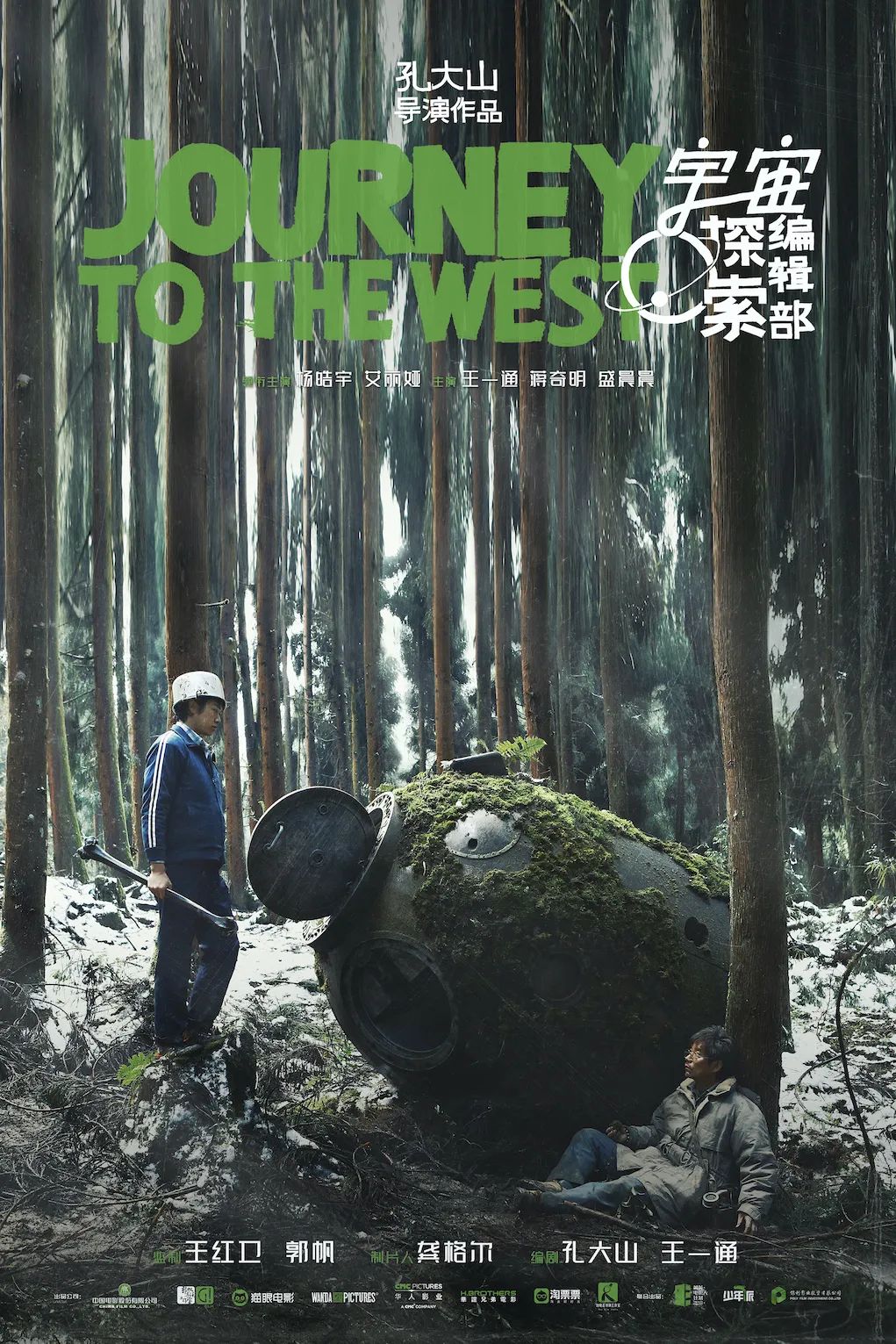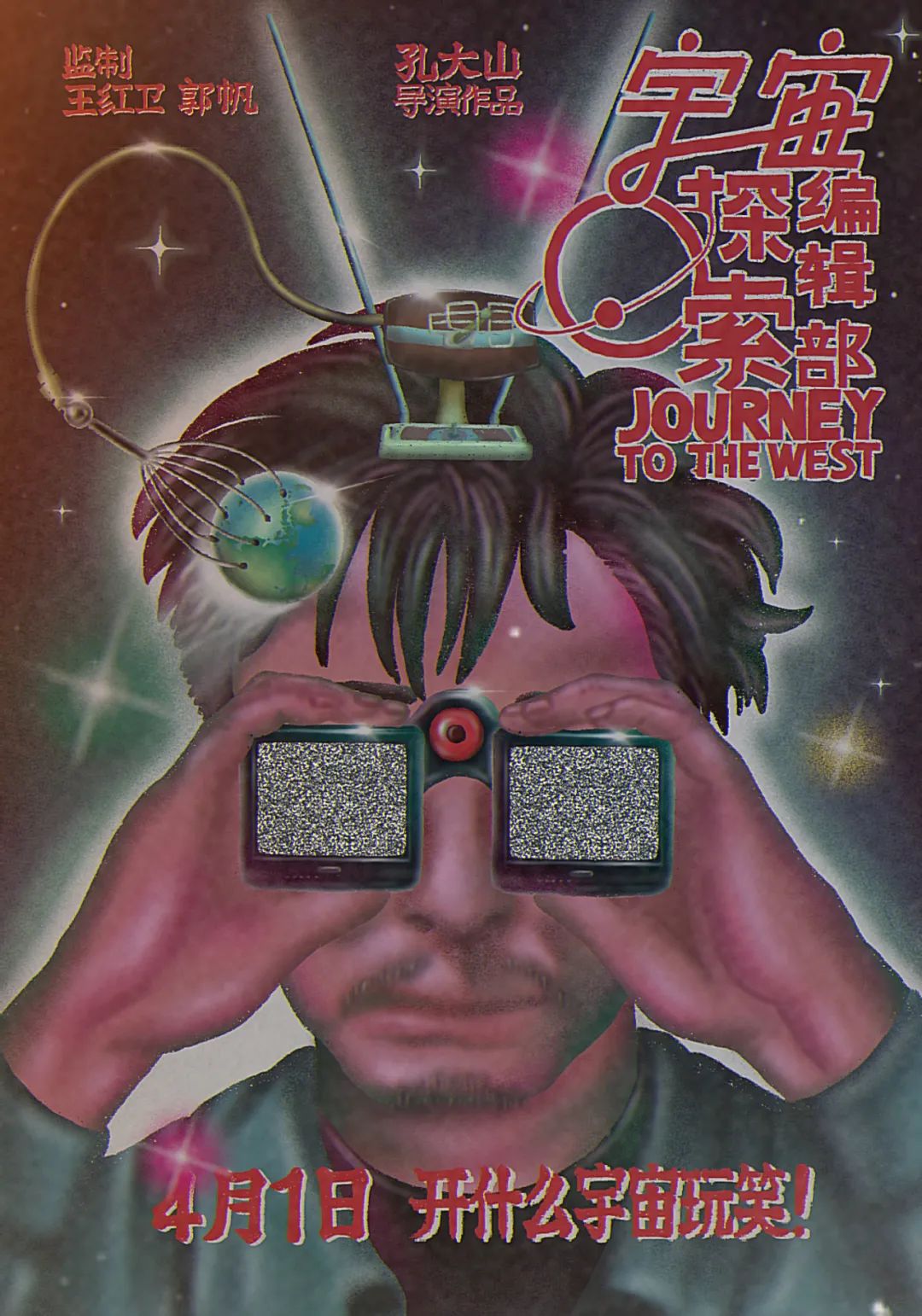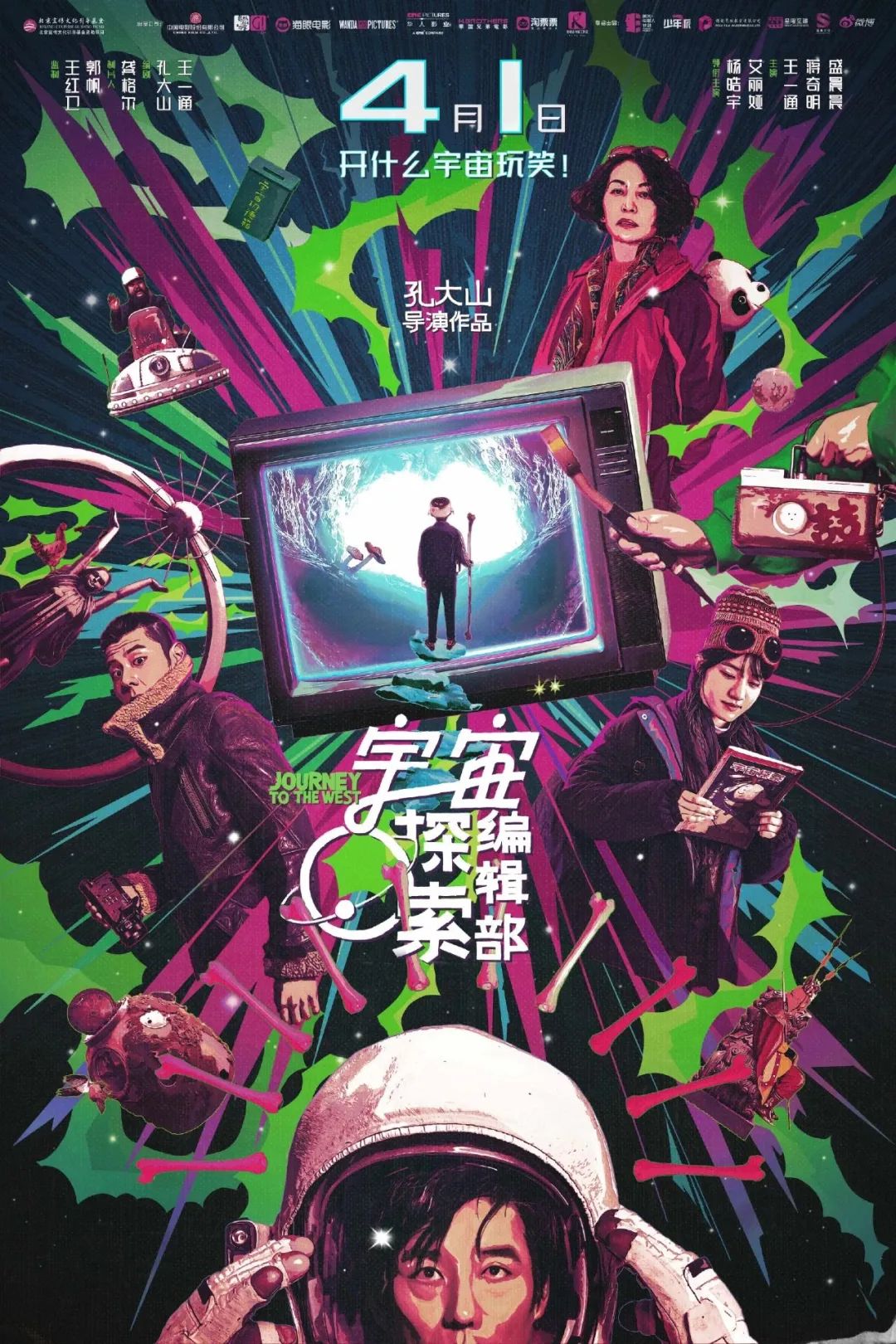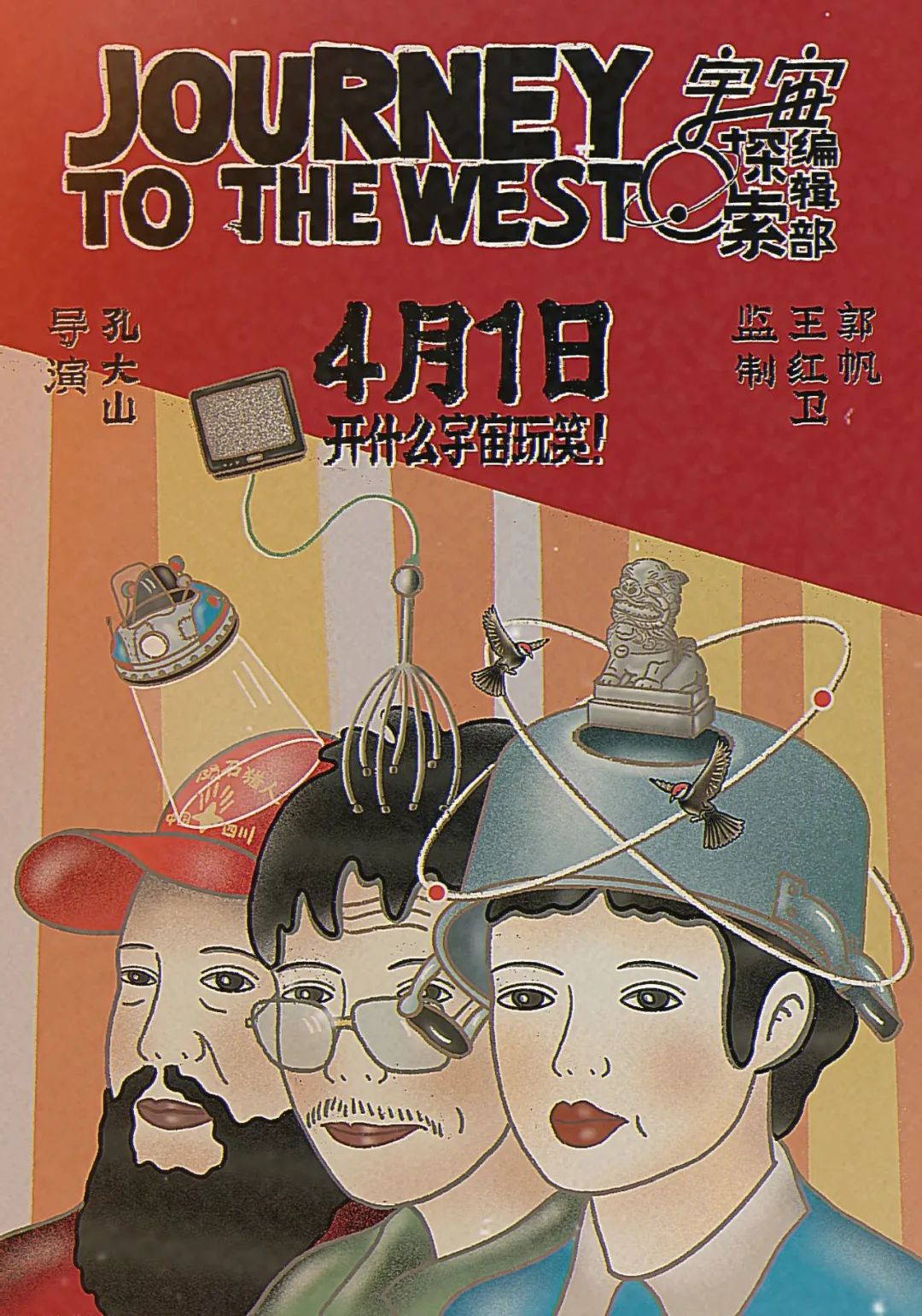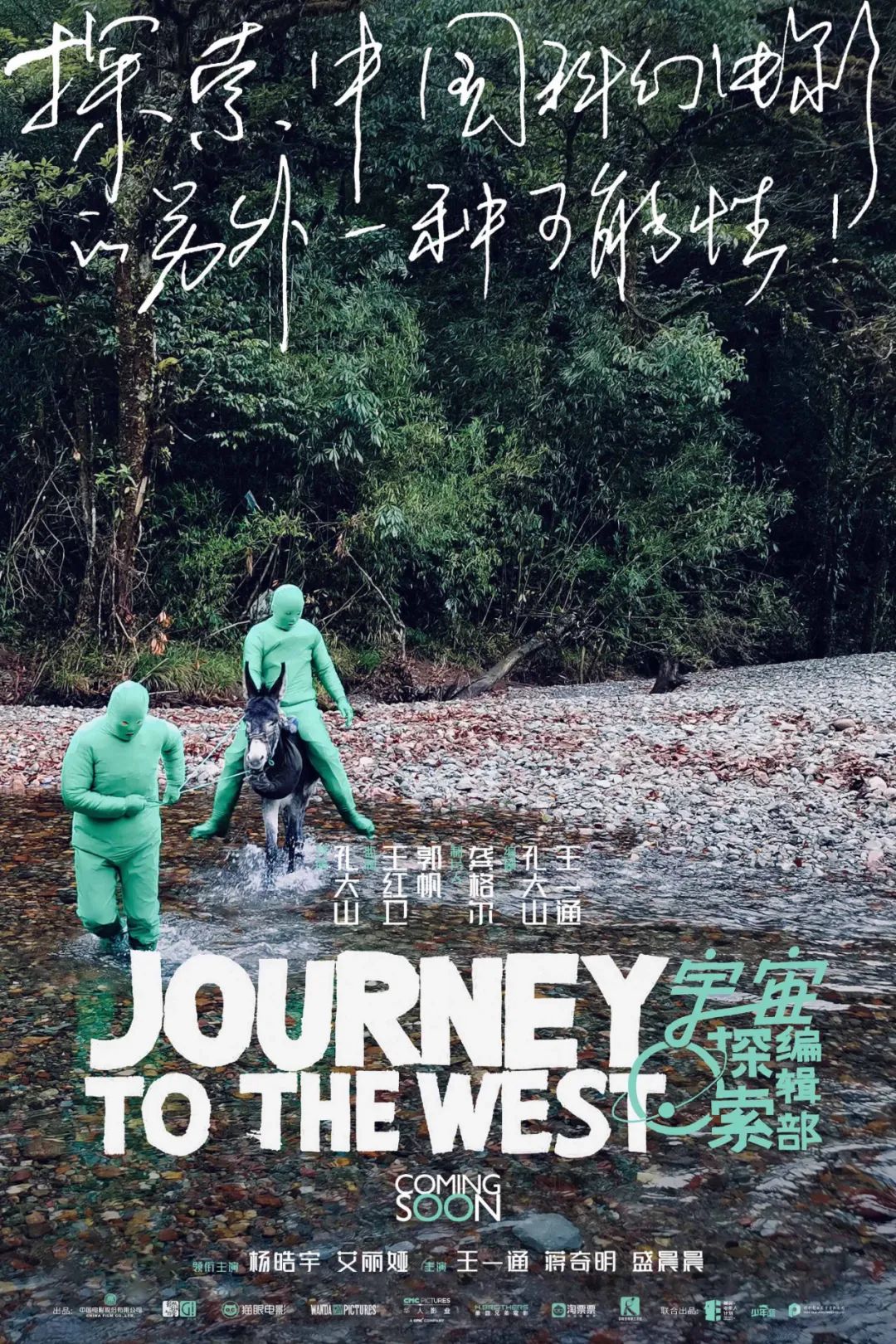
这可能是近期国内最“疯”的电影海报了
虽然《宇宙探索编辑部》已经上映快一个月了,但留给柚子的“后劲”依然十足,你可以说它荒诞无厘头,也可以说它是精神病药方,更可以说它毫无意义,浪费时间……
无论哪种,都注定了这是一部很“疯”的电影,如果你还没有找到宇宙的意义,那今天就跟我一起神游一下~
宇宙海报
虽然是一部小众科幻片文艺片公路片,但在片名设计上丝毫不马虎,“宇宙”加入了星球元素,中文笔画也配合着拉了个“轨道”,其它字形是手写的,既不影响辨识度,同时也不会太工整,就像这部电影的镜头一样。有意思的是英文翻译,“journey to the west”,本身就是西游记的意思,也算是妥妥的透题了。
首先它是一个伪科幻片,千万别被这个不明球型装置骗了(海报有点致敬环形物语)。
但它也不是一个文艺片,它融合的元素比较多,你可以通过这张海报一探究竟(有点像瞬息全宇宙)。
其它的海报,只要你仔细看,也会发现玄机,比如孙一通拿着那根变长的“外星人骨头”。
比如出现过好几次的DNA双螺旋,最后还成为宇宙的一段……
比如那句浪漫的台词,“这不是普通的电视雪花点,这是宇宙诞生的余晖”。
这张“开脑洞”的海报剧透更多,唐志军、孙一通、陨石猎人分别带着连接雪花电视的接收器、麻雀环绕的石狮子、宇宙飞船,与宇宙“亲密接触”,画风也是那种浓浓的复古感,让我想起了80年代的动画片。
既然是西游记,那就必须是唐僧(唐志军)、孙悟空(孙一通)、猪八戒(秦彩蓉)、沙和尚(那日苏)、晓晓(白龙马)都在。
这张就更有西天取经的意思了,只不过西游记取的是真经,宇宙小分队的目标是外星人。
当你以为这是一部大杂烩电影时,它又开始了走心了……
最后这张关机海报,是认真的吗?哈哈哈